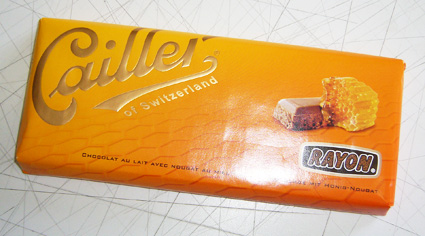
Triumph – Neues Logo
In einem ersten Schritt wurde eine Markenplattform erarbeitet und eine einzigartige Markenidee definiert, die zum einen die Herkunft, Kompetenz und die Erfahrung des Unternehmens, zum anderen die Zielgruppe der modernen, selbstbewussten Frau herausstellt.
genauso ist es, heinrich. ein guter grafiker zu sein ist heutzutage unwichtig.
du brauchst nur einen gut trainierten marketingtypen der mit buzzword-
floskeln um sich haut und alles perfekt redet. das design ist zweitrangig.
Meistens ist das wohl so. Dass nach dieser Belaberung die Wirklichkeit zuweilen aber auch anders entscheidet, hat ja Nestlé Schweiz vergangenes Jahr mit einiger Marktmacht zu spüren gekriegt. Zur Erinnerung: Der Relaunch der Schokoladen-Traditionsmarke "Cailler" im Frühjahr 2006 hatte bis in den Herbst einen so gottvergesslichen Umsatzeinbruch zur Folge, dass man subito einen Relaunch-Relaunch 8) auf dieses Frühjahr aufgleiste. Die Kosten für diesen Lehrgang schätze ich mal auf insgesamt weit über hundert Millionen Schweizer Franken ... Gründe für die Ablehnung im Markt waren nicht zuletzt auch das Packungsdesign und die Materialwahl.
Erwähnenswert in diesem Zusammenhang waren die Reaktionen der Nestlé-Cailler-Vermarkter im Umgang mit den abertausenden Beschwerden: Auf mein Mail beispielsweise (ich bemängelte vor allem den ökologischen Unsinn, Schokolade in hochwertigen Kunststoff zu verpacken) hatte ich damals innert einer halben Stunde eine ausführlich-ehrliche Antwort, fünf Tage später eine Packung feinste Cailler-Pralinen "zum Trost" und dieses Frühjahr kriegte ich zur Ankündigung des Relaunch-Relaunch gleich nochmals Schoggi-Post.
Zur Ergänzung: Entworfen hatte die neuen, nun wieder reumütig zurückgezogenen Verpackungen der Stararchitekt (!) Norman Forster…
Excusez-moi, lieber FlorianG, aber der Brite Sir Norman Foster hat da höchstens über Frankreichs Jean Nouvel gelacht, nach diesem Debakel ...
die geschichte ist mir neu. hast du bilder davon?
wie sah die verpackungvorher aus und wie sieht sie jetzt aus?
Danke Heinrich. Genau so kam sie im Frühjahr 2006 daher.
Heute sieht ein Teil des Sortiments wieder so aus (Scheisse, hier ist's so warm, die Schokolade rinnt gleich aus der Packung ...)
Momentan haben die einen Packungsmix. Zu sehen in der Rubrik "sortiment" unter
Beachtet auch, wie sich die Wortmarke wieder dem Urzustand annähert (Wortmarke ca. 1931).
Alles klar, Florian und wie auch immer ... die Moral von dieser G'schicht?
Architektur ist zwar hoch im Bau aber zum Essen nicht.
Bevor hier die Diskussion losging sah ich das neue Logo von Triumph und dachte so schlecht ist es nicht. Ich fand es nimmt die Anmutung des alten Schriftzuges auf – in einer zeitgemäßen Variante. Und eigentlich hat sich daran nichts geändert. Eingebettet in einen neuen Auftritt wird die Verbindung von alt nach neu wohl unspektakulär gelingen.
Ich verbinde mit der Marke allerdings kaum etwas. Nur, dass ich immer die Assoziation von Kakao habe – ob sich das ändert weiß ich allerdings nicht :roll: